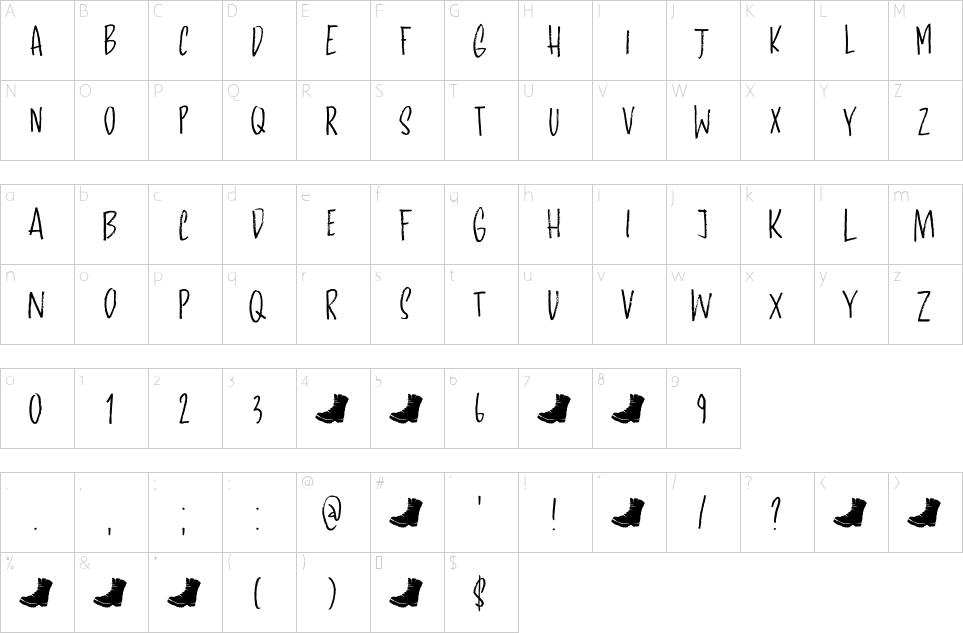
A Gritstomper é uma linda e robusta fonte que adicionará profundidade a qualquer projeto gráfico que você estiver desenvolvendo. Feita pelo designer Hanoded, essa fonte foi projetada para oferecer um visual único com linhas fortes e interessantes. Seu design agressivo combina harmoniosamente com várias tipografias modernas, tornando-a uma escolha ideal tanto para aplicativos de texto como para títulos em sua próxima criação digital. Com uma versão para Windows e Mac disponíveis, a Gritstomper é fácil de integrar ao seu ambiente de trabalho ou projeto. Sua popularidade entre os designers pode ser medida em 1491 downloads desde sua publicação, indicando o valor e a qualidade deste fonte. Se você busca algo que seja tanto funcional quanto original para dar um toque diferenciado a seus projetos gráficos, a Gritstomper será uma excelente escolha.